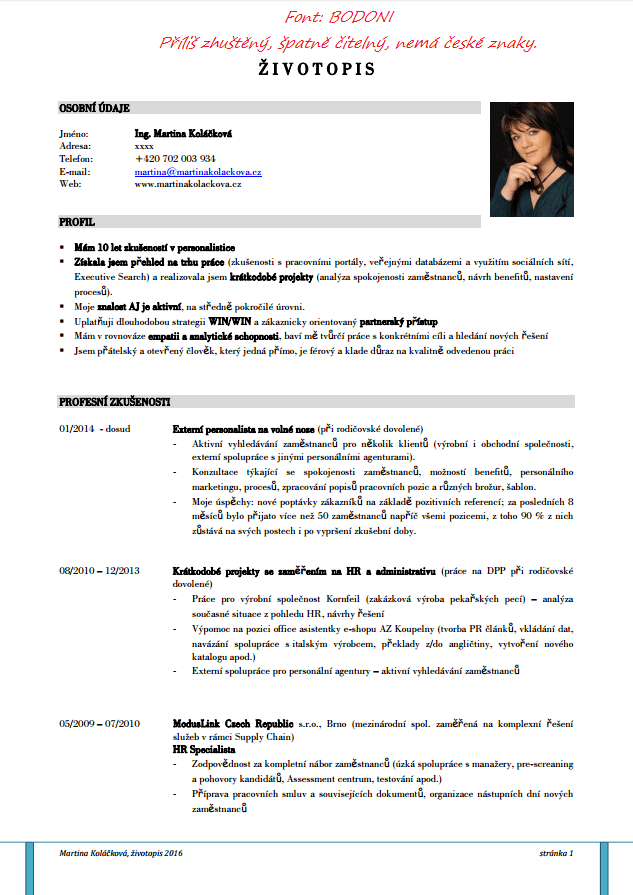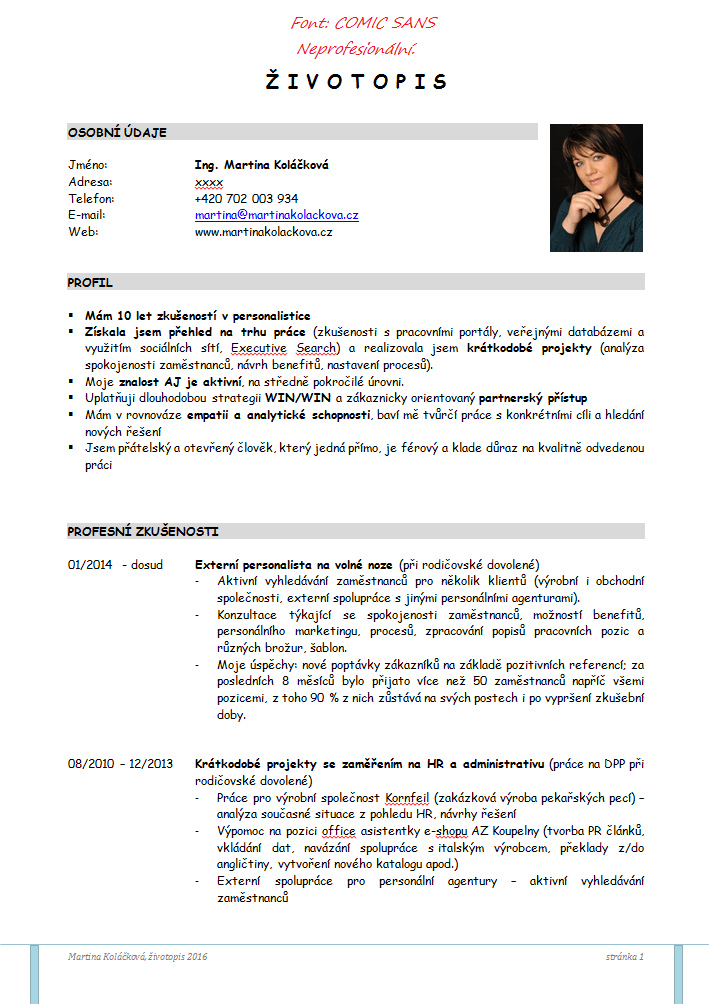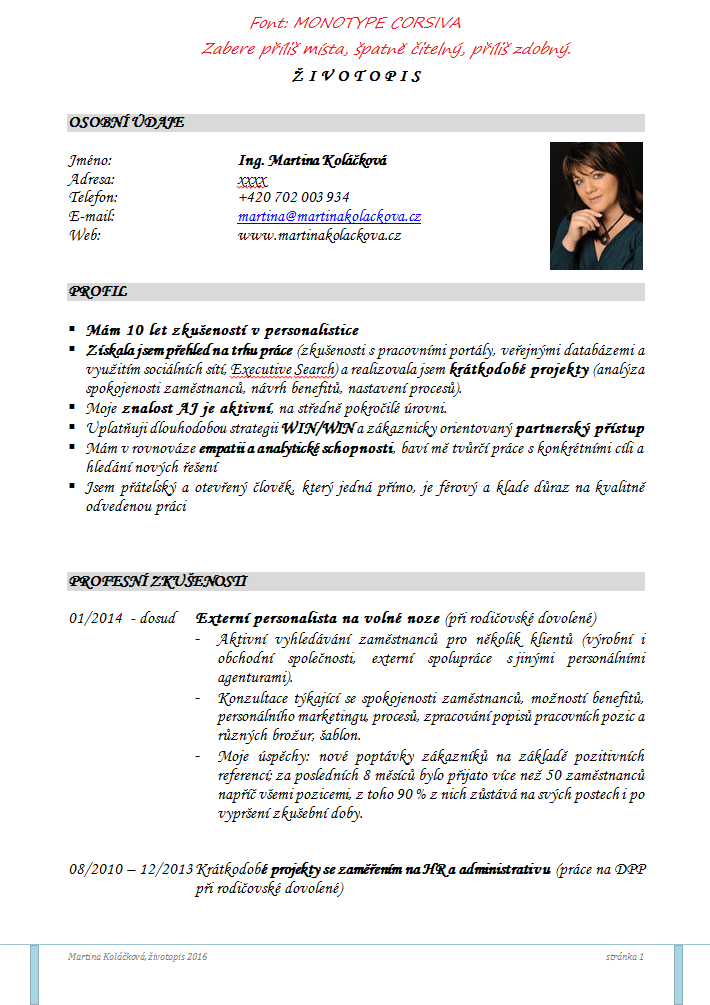
Hraje výběr fontů pro životopis významnou roli?
„Tím, že používáte špatný font, můžete na lidi působit nesprávným dojmem a to může mít vliv na rozhodnutí, která utvářejí vaši budoucnost.“
Aric Sigman, psycholog
Tato věta kdysi způsobila, že můj zájem o fonty získal další rovinu – psychologickou. Mnohokrát mne napadlo, jak by se znalost psychologie fontů dala využít v personalistice. Font, který zvolíme, o nás hodně vypovídá, takže volba fontů v životopise jednoznačně vypovídá o charakteru a osobnosti uchazeče. Navíc v rovině podvědomí, kterou on sám většinou nevnímá a tím pádem ani nemá tendence ji ovlivňovat. Kdyby to nebylo takové klišé, napsala bych „Můžeme v něm číst, jako v otevřené knize.“.
Aric Sigman uvádí příklad, že do solidní zavedené firmy, která podniká v „seriózním“ oboru (např. finance, bankovnictví, atd.) by rozhodně poslal životopis napsaný patkovým fontem. Naopak do životopisu  pro zájemce o práci v mladé, dynamické firmě (IT, marketing,…) by použil bezpatkový font. Studovala jsem psychologii fontů u desítek lidí a jsem si jistá, že toto tvrzení má své opodstatnění. Když porovnám jejich charaktery, hodnoty a priority, tak je zřejmé, že lidé s podobným charakterem si vybírají podobné fonty. Není v tom žádná magie. Reagují prostě stejně na vizuální charakteristiky fontu. Vědomě je nevnímají, ale podvědomě ano. A pokud tak reagují všichni lidé, nebudou výjimky ani personalisté.
Dovedu si představit, že znalost psychologie fontů by jim mohla dát do rukou další důležitý argument, podle kterého vybrat toho nejvhodnějšího uchazeče. Věděli by, zda se hodí pro manažerskou funkci, dokáže vést lidi a nést zodpovědnost anebo jestli spíše rád komunikuje a bude výborným školitelem. Poznali by puntičkáře anebo naopak člověka, který má v sobě kreativního ducha.
Prostě by věděli, kdo se bude výborně hodit pro jakou práci.
Samozřejmě, ne každý člověk si dá v životopise práci s výběrem fontů a ne každý personalista má chuť nad tím přemýšlet. Ale náhodou jednu takovou osobu znám.
Jmenuje se Martina Koláčková, pracovala jako personalistka v korporátní sféře a zaujala mne článkem nazvaným: „Když zakomponujete do inzerátu konkrétní energii, přitáhnete tím právě toho, kdo takovou energii hledá“. Jasně, to je ono. A je jedno, jestli tu energii do životopisu zakomponujete pomocí barvy, výběru slov, nebo fontů. Ono je to totiž stále jedno a to samé.
A tak jsem se jí zeptala, jak je na tom s fonty ona. Třeba vám rozhovor přinese inspiraci, nebo námět k zamyšlení. A jsem si jistá, že až příště budete psát životopis, tak si na něj vzpomenete.
ROZHOVOR S MARTINOU KOLÁČKOVOU:
Martino, vím, že je pro tebe velmi důležitá vizuální stránka textů a dokumentů. Z jakého důvodu?
Já osobně mám vrozený cit pro detail a vím, že na mě intenzivně působí různé kombinace barev, obrázků a textů. A jsem přesvědčená, že působí na podvědomí nás všech, jenom někteří z nás si to uvědomují víc a někteří téměř vůbec. Je proto jasné, že když na mě tímto způsobem působí okolní vjemy, tak i já můžu podpořit svůj message/svoji myšlenku tím, že ji obalím do vizuálu, který podporuje to, co chci sdělit.
Když tak nad Tvojí otázkou přemýšlím, napadají mě 2 body:
1. Vizuální stránka dokáže přenášet emoce mnohem více, než jenom samotný text. Je v tom podobný princip, jako když prožitou zkušenost vnímáte mnohem více, než když něco jenom vidíte anebo jenom slyšíte. Zapojujete více smyslů, působíte na podvědomí.
2. Když jsou všechny složky v harmonii (obsah a název dokumentu s obrázkem a barvou), pak všechno působí důvěryhodněji. Všichni to známe – obal nás hodně ovlivňuje. Když je obal škaredý, ani ten produkt neodzkoušíme. Naopak, pokud je krásný obal a obsah je o ničem, pak se dostaví pocit zklamání.
Jakou roli v dokumentech pro tebe hrají fonty?
Musím se přiznat, že nad fonty jsem začala vědomě přemýšlet až v nedávné době. Vliv obrázků a barev jsem vnímala vždycky intenzivněji. Myslím si, že je to dané tím, že texty na internetu a v knížkách měly vesměs standardizované fonty, které mě nijak nerušily. Prostě zapadaly do konceptu.
Dnešní technologie umožňují vytvářet si na internetu vlastní prezentace, vlastní weby a různé materiály pro inzerci nebo jen tak pro zábavu. Už to není jenom oblast pro odborníky, ale pro širokou veřejnost. V tomto okamžiku jsem si začala postupně uvědomovat, že určité typy písma mi prostě vadí. Pak se nedokážu přinutit číst obsah, i kdyby byl sebehodnotnější.
To mě přesvědčilo o tom, že fonty nás ovlivňují velmi podobně, jako je to u obrázků nebo barev. Když jednotlivé složky (obsah, obrázek, barva, font) nejsou v harmonii, bude nás to podvědomě dráždit, byť nevíme proč.
Vnímáš, jaký font použil uchazeč v životopisu? Může to mít vliv na to, jak na tebe zapůsobí a jestli ho vybereš?
Dneska už ano. Font má totiž tu moc, že dokáže z dobře napsaného dokumentu udělat pocitově hromadu nepřehledného textu, který se nechce nikomu číst. A přitom často stačí překlopit dokument do jiného typu písma a najednou působí životopis vzdušně, přehledně a ta moje nechuť se do něj začíst je pryč.
2. Všetko o fontoch je podľa mňa veľmi zaujímavé…asi preto, že o nich viem veľmi málo. Rozvíjajte túto vedeckú oblasť, prinesie do života krásu, estetiku, nežnosť.